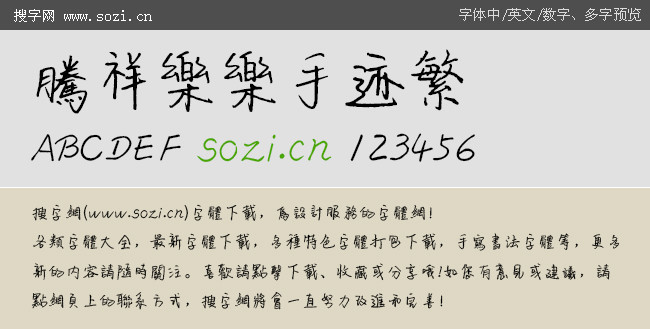
騰祥樂樂手跡繁
搜字網(wǎng)提供一款騰祥樂樂手跡繁中文藝術(shù)字體下載,騰祥樂樂手跡繁是一款很漂亮的手寫字體,書寫風(fēng)格自然流暢,獨(dú)具風(fēng)格,稚拙中透顯出活潑靈動的氣息;無雕琢,無拘束質(zhì)樸的視覺效果,用于正文更體現(xiàn)出手寫自然之感。字體可以廣泛應(yīng)用于印刷出版、包裝設(shè)計、廣告設(shè)計、網(wǎng)頁設(shè)計等領(lǐng)域。